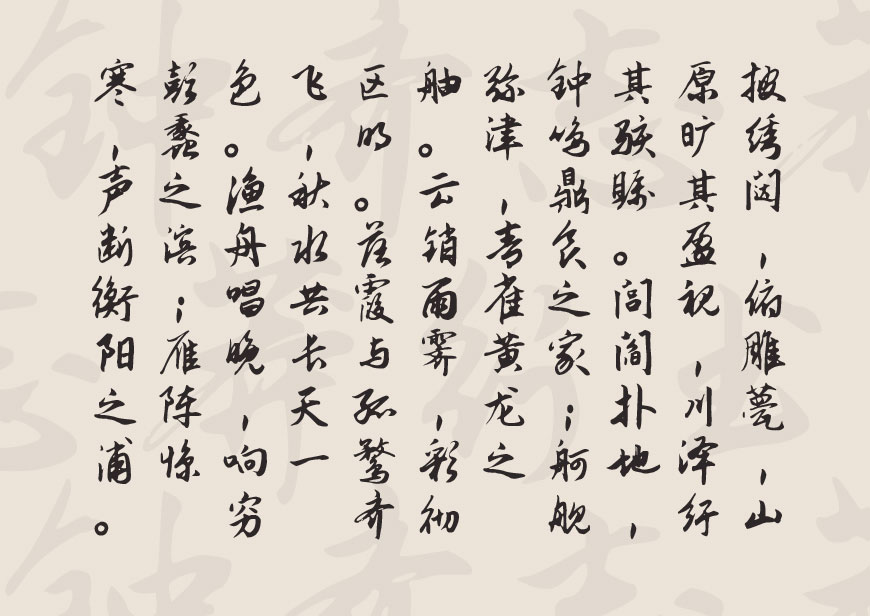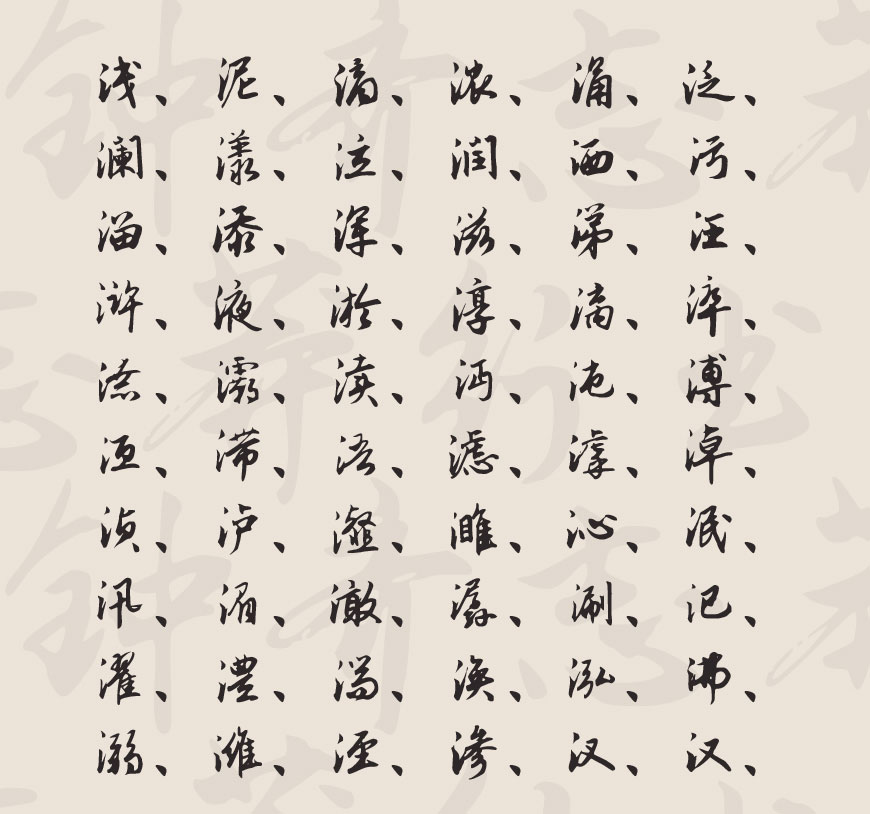
钟齐志莽行书
钟齐志莽行书是谷歌开源字体项目里的一款中文行书书法字体,遵循SIL Open Font License 1.1授权许可,是由上海钟齐字库公司根据书法家韦志莽先生的毛笔书法开发而成。志莽行书这款字体字形潇洒飘逸,形体端秀而骨架劲挺,整体效果非常出色,钟齐志莽行书字体可广泛用于广告设计、包装设计等方面。